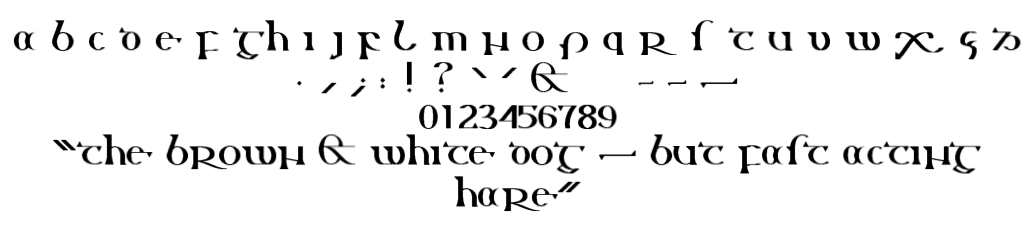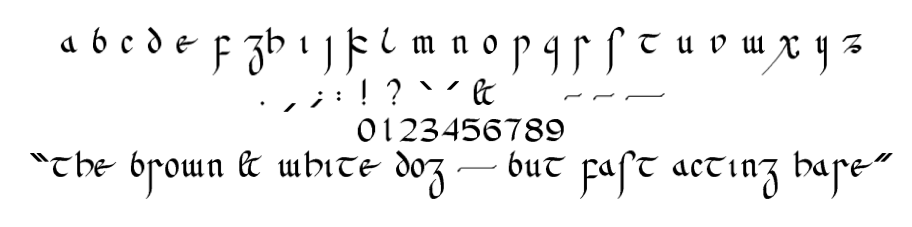
Ernsthaftes Anliegen: Wie setzt man korrekt Fraktur, wenn doch die Zielgruppe weder mit den Ligaturen, den Sonderzeichen wie ß (auch dem kleinen) und deutschen Umlauten nichts anfangen kann? Weil sie nämlich Englisch spricht und denkt bzw. Amerikanisch?
Ich verrat’s schon mal: Es geht um das umstrittene (ja? bei wem?) »Handbuch der Frakturschriften«, das ich in die englische Sprache übertragen möchte: »Manual of Blackletters«. Im Gegensatz zum eher spielerischen Umgang mit dieser Schriftensippe im Buch »Fraktur mon amour« handelt es sich sich hierbei um den Versuch einer so weit wie nur irgendwie möglichen Übersicht über alle jemals herausgebrachten Frakturschriften.
Der Herausgeber wird auch nicht Delbanco sein, sondern ein englischer Verlag. Seite 59 wird auf meinen ausdrücklichen Wunsch hin gestrichen. Politische Aussagen haben IMNSHO in einem Fachbuch nichts zu suchen.
Fraktursatz sollte sich imo nach den gebräuchlichen Regeln der Anwender(zeit) richten, vielleicht mit der Ausnahme des Lang-S.
Oder Du suchst Dir einen beliebigen Punkt in der Orthographie-Geschichte, erklärst diesen als Point of No Return, ab dem alles nur noch den Bach runtergeht und alles davor für sakrosankt.
Oder Du forschst nach statistischen Häufungen in Deiner Zielsprache (BE und AE haben durchaus unterschiedliche Entwicklungen) und entwickelst daraus eine Orthographie.
Danke, den Thread habe ich jetzt komplett gelesen. Das Dumme an diesen Internet-Diskussionen ist, dass das Thema grundsätzlich zerfledert wird, bis nur noch Fetzen vom Armgelenk herunterhängen, die eigentliche Frage aber so gut wie nie abschließend beantwortet werden kann.
Hilfreicher als jeder Link auf wiederum nur ungares Gebrabbel wäre jedoch die konkrete persönliche Aussage gewesen, Ralf. Und da Du Dich glaube ich besser mit aktuellen Trends auskennst als ich, bitte ich ganz konkret um Deine und Eure Empfehlung in diesem Fall. Und – ja – ich habe auch den Wikipedia-Artikel fast komplett gelesen.
Ich persönlich neige dazu, das Lang-s eher wegzulassen, da wir ja im Gegensatz zur ersten (deutschen) Auflage nunmehr den Weltmarkt ansprechen. Das »ß« fällt dann auch besser weg, das versale ohnehin. Die Ligatur »st« werde ich nicht verwenden und auch nicht die echten Umlaute, sondern stattdessen ae, ue, oe.
Meines Erachtens geht es *nicht* darum, mich für eine bestimmte Festlegung zu entscheiden, die im Übrigen so rein gar nichts mit Orthografie zu tun hat. Das ist Satztechnik reinsten Wassers, aber ich kann doch, nur weil ich selbst ein Deutscher bin, nicht dem Rest der Welt deutsche Regeln verordnen.
Ich personlich würde dort, wo englische Texte in Fraktur gesetzt werden sollen, auch eine typisch englische (Old English) Blackletter verwenden, und dann vielleicht eine Tabelle der jeweiligen Stile der gebrochenen Schriften mit ihren besonderen, möglicherweise missverständlichen Buchstabenformen und Ligaturen.
Schließlich gibt es ja ähnlich wie in den in Deutschland gebräuchlichen gebrochenen Schriften, mit dem oft als U missverstandenen Am, dem schlanken k, dem aus dem r mit Swash gebildetem x und dem oft als k fehlgedeutetem tz ja auch für unsere Augen ungebräuchliche Formen in den insularen gebrochenen Schriften, z.B. f, g, r, t:
PeterRWilson-InsularMiniscule-2000-2003.
PeterRWilson-InsularMajuscule-2000-2003.
Ernsthaftes Anliegen: Wie setzt man korrekt Fraktur, wenn doch die Zielgruppe weder mit den Ligaturen, den Sonderzeichen wie ß (auch dem kleinen) und deutschen Umlauten nichts anfangen kann? Weil sie nämlich Englisch spricht und denkt bzw. Amerikanisch?
Ich denke nicht, dass es irgendeine spezielle Ausprägung des Fraktursatzes gibt, die im Englischen mit irgendeiner Berechtigung »korrekter« anzusehen ist als irgendeine andere, da der Fraktursatz schon lange ausgestorben ist und deutlich weniger gegenwärtig ist als im Deutschen. (Etwas anders ist es mit gebrochenen Schriften im Allgemeinen, um die es hier aber nicht geht, wenn ich das richtig verstehe.)
Ich frage mich, wo Probleme mit dem Eszett oder den Umlauten entstehen sollten, da sie in der englischen Sprache eh nicht auftauchen. Die einzige Ausnahme sind deutsche Eigennamen oder Beispiele, die der Leser sowieso nur dann verstehen kann, wenn er des Deutschen mächtig ist, in welchem Falle ihn ein Umlaut oder Eszett auch nicht stören sollte.
Letzten Endes hängt die Frage, wie Du etwas setzt davon ab, welches Publikum Du erwartest:
• Wenn Du möchtest, dass das alles möglichst einfach zu lesen ist, darfst Du den Text gar nicht in Fraktur setzen – was natürlich in einem Buch über Fraktur etwas seltsam ist.
Au weia, was habe ich da bloß ausgelöst hier!
Selbst die deutsche, fertige Ausgabe des Handbuchs enthält im Fließtext *keine* Fraktur. Das hätte ich schreiben müssen. Der Verleger wollte das zwar ursprünglich gern, jedoch haben der Verfasser und ich ihm das ausreden können. Verwendet haben wir stattdessen die »Palatino« von Linotype, nur für die Headlines die »Wohe-Fraktur«.
Aber auch »nur« für diese war meine Frage berechtigt und ist auch von Euch gründlich diskutiert und gelöst worden.